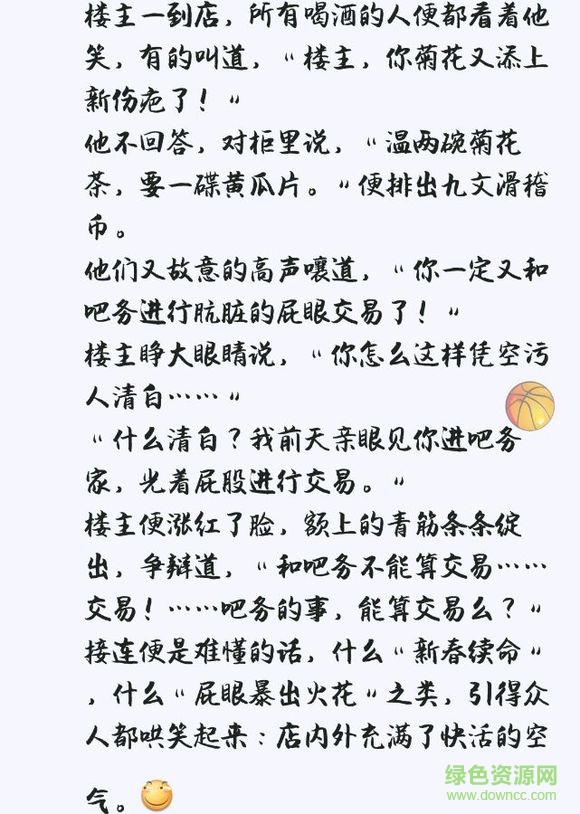
aa潤(rùn)行體是一款造型流暢潤(rùn)滑的書(shū)法字體,有著很高的辨識(shí)度和美感,適合于書(shū)面印刷、文本打印、廣告設(shè)計(jì)等行業(yè),需要的朋友請(qǐng)來(lái)綠色資源網(wǎng)免費(fèi)下載吧!
潤(rùn)行體字形對(duì)稱(chēng)、筆畫(huà)飽滿(mǎn),因顯和潤(rùn),顧得此名。